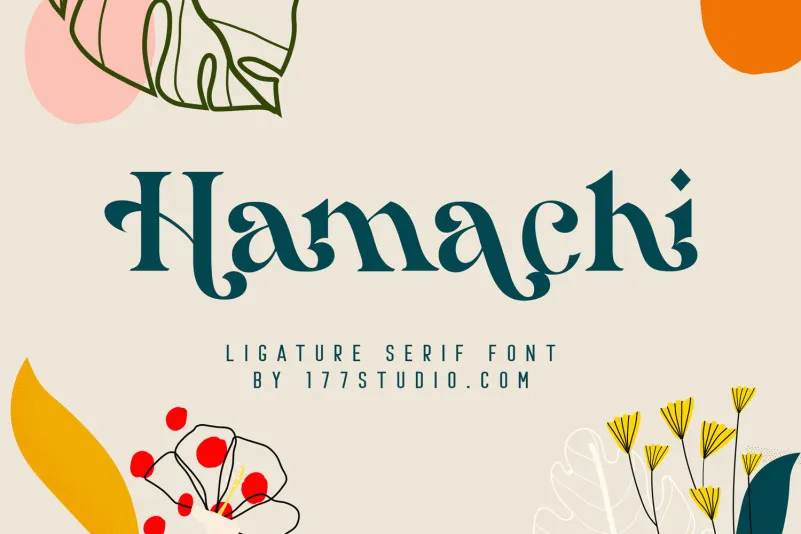
Hamachi Font
Descobrimos uma nova serif chamada Hamachi que traz ligaturas modernas para a gama dos tipos elegantes e únicos. Esta fonte é simples na aparência, mas possui um caráter inigualável – uma combinação de beleza, simplicidade e elegância. Os designers da 177Studio criaram uma fonte que permite à sua escrita ganhar nuances atraentes sem precisar de muito esforço. Hamachi é perfeito para aplicativos como logotipos, cartas de convite, headlines ou qualquer outro recurso gráfico onde você deseja transmitir seu estilo e personalidade através da tipografia. Aproveite e descubra o poder inigualável dessa fonte versátil em sua próxima criação.